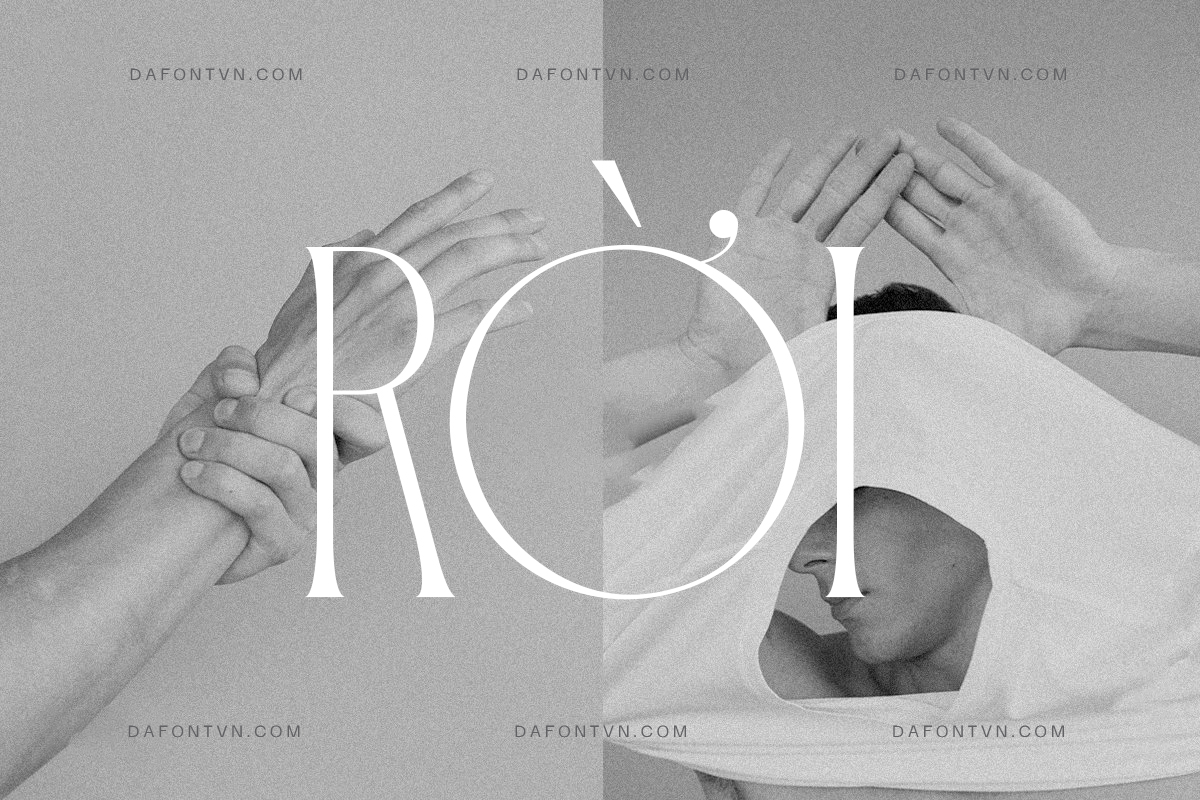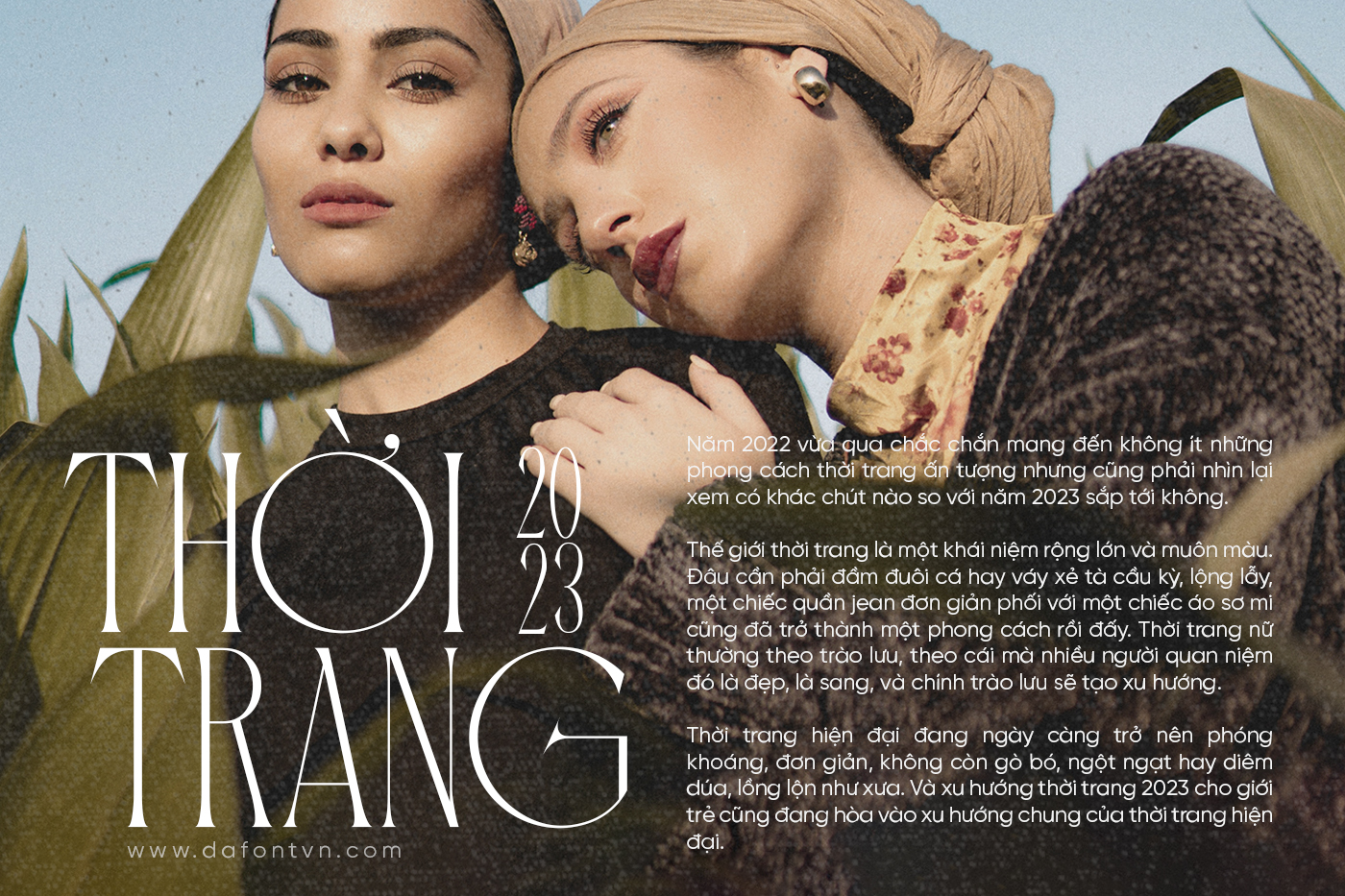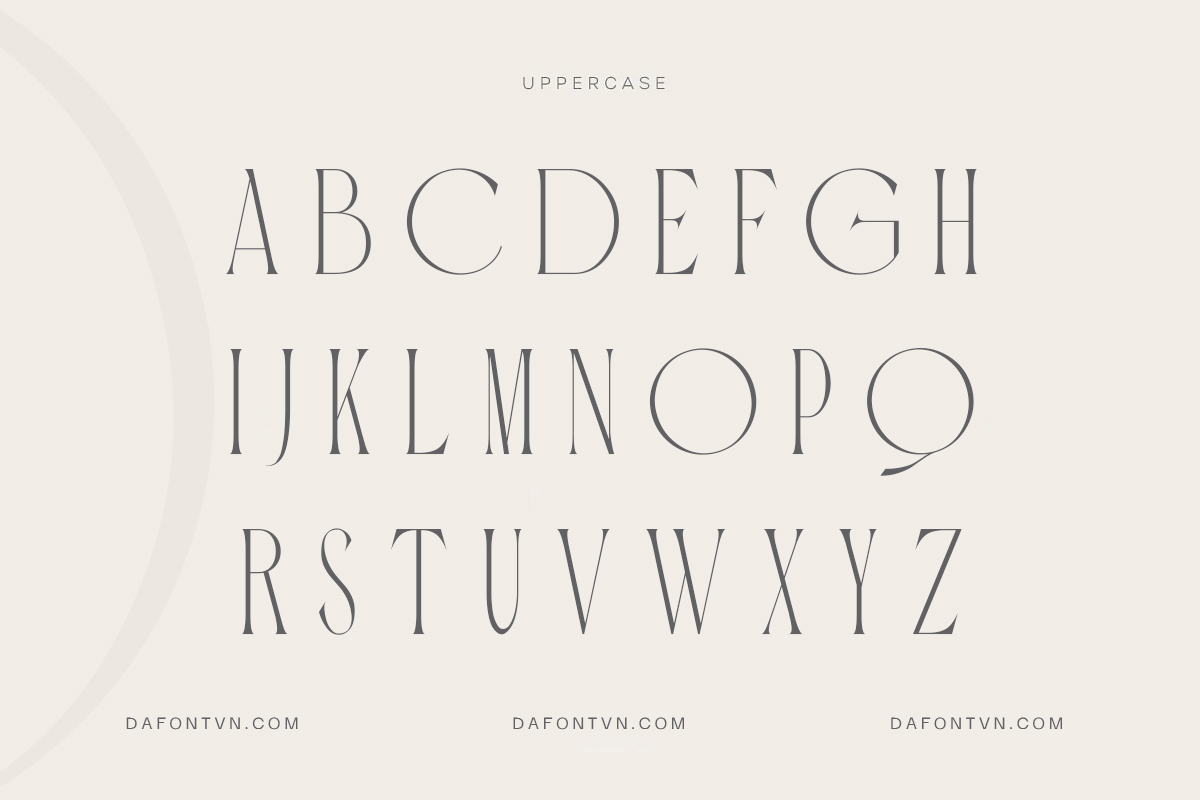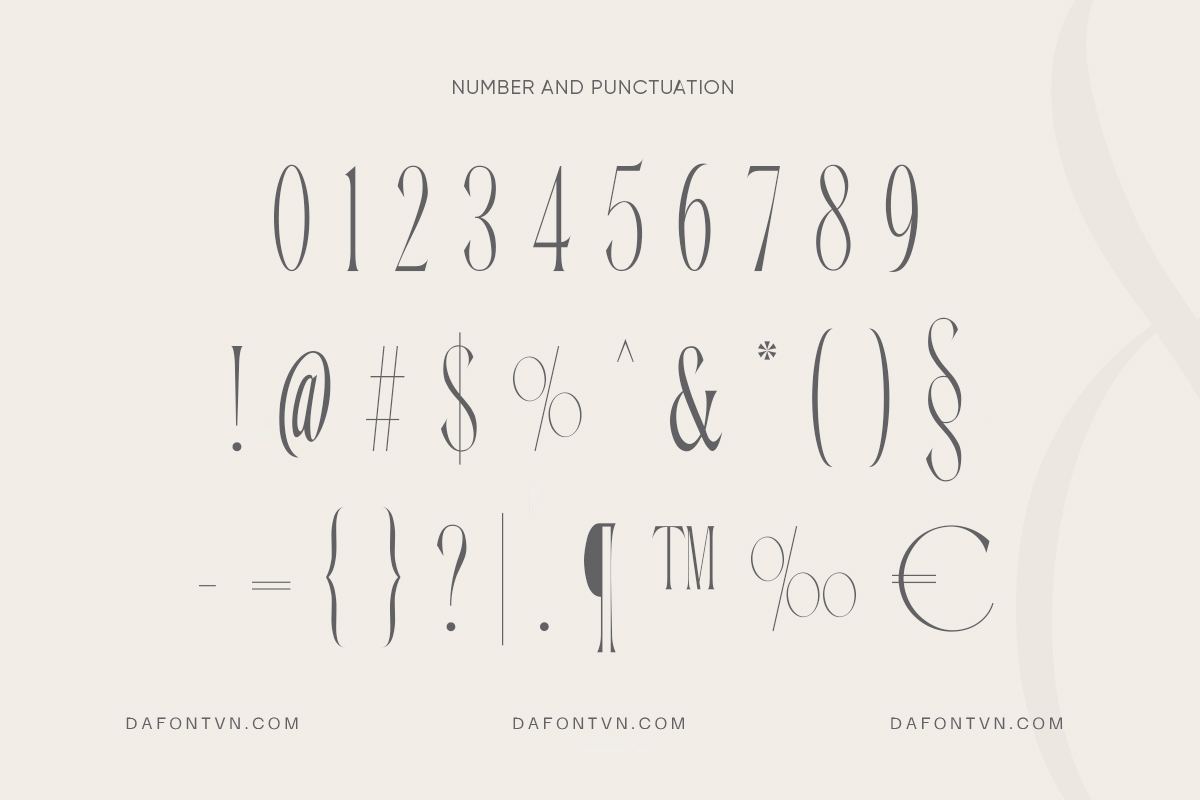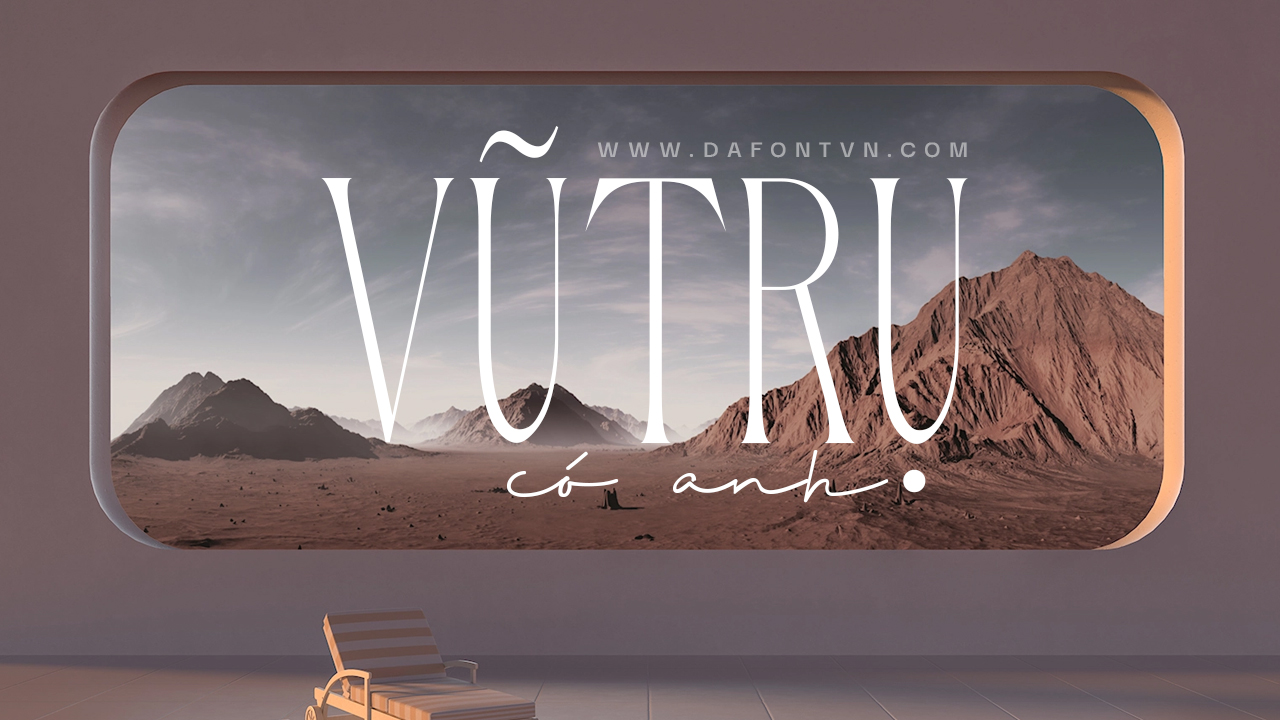
Carola – Modern Serif là một kiểu chữ hiện đại với các nét chữ in hoa và các nét chữ được thiết kế cao, mảnh ấn tượng. Font Carola Việt hóa phù hợp cho rất nhiều thiết như áp phích, thiết kế web, thời trang, xây dựng thương hiệu, tạp chí, thiệp mời, bìa sách và một số tác phẩm khác.